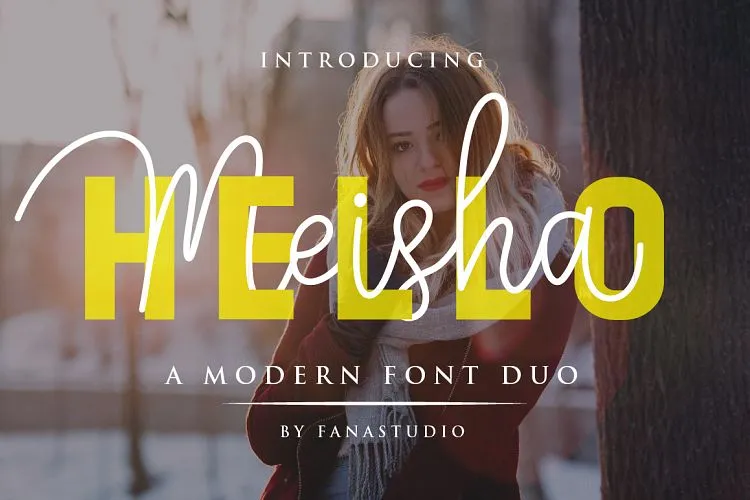
Hello Meisha Font Duo – Download Grátis
Olá amantes do tipo! Presenteamos-vos uma nova dupla de tipos com traços suaves, composta por um script elegante, estilo firma e um tipo serif moderno, all-caps, elegante e sofisticado. Introduzimos o Hello Meisha Font Duo, um estilo fresco para seus projetos de arte mais recentes. O Hello Meisha Font oferece uma mistura única de elegância, classe e modernidade. Este belo script font é a sua maneira de personalizar as suas próximas criações artísticas com um olhar refinado e contemporâneo. Não perca esta oportunidade de adicionar seu próprio toque criativo ao seu próximo projeto gráfico. Você não vai encontrar nada como isso em nenhum lugar. Experimente-o agora!